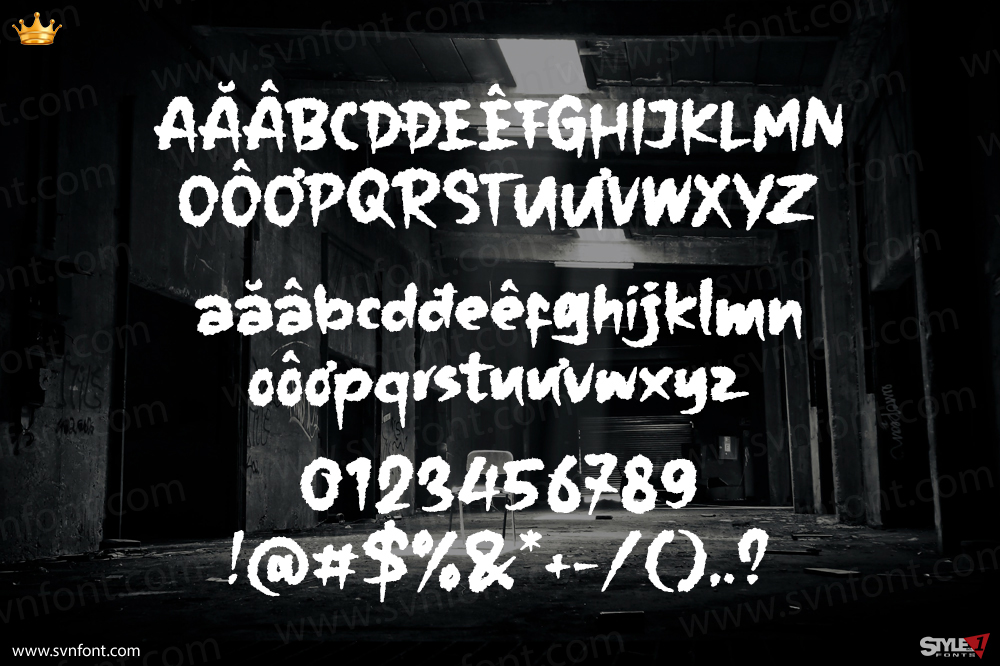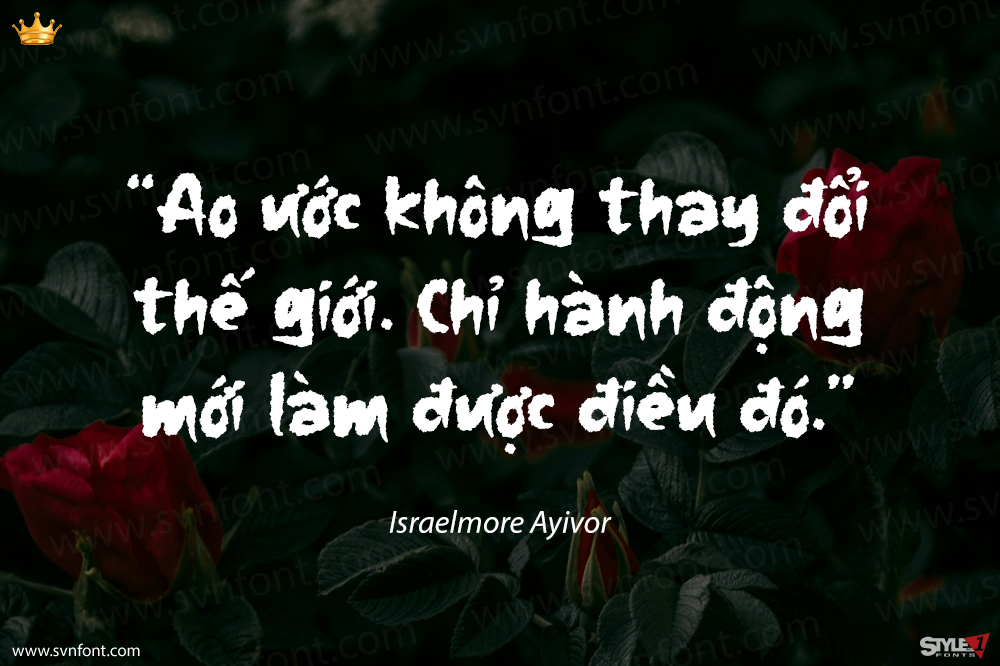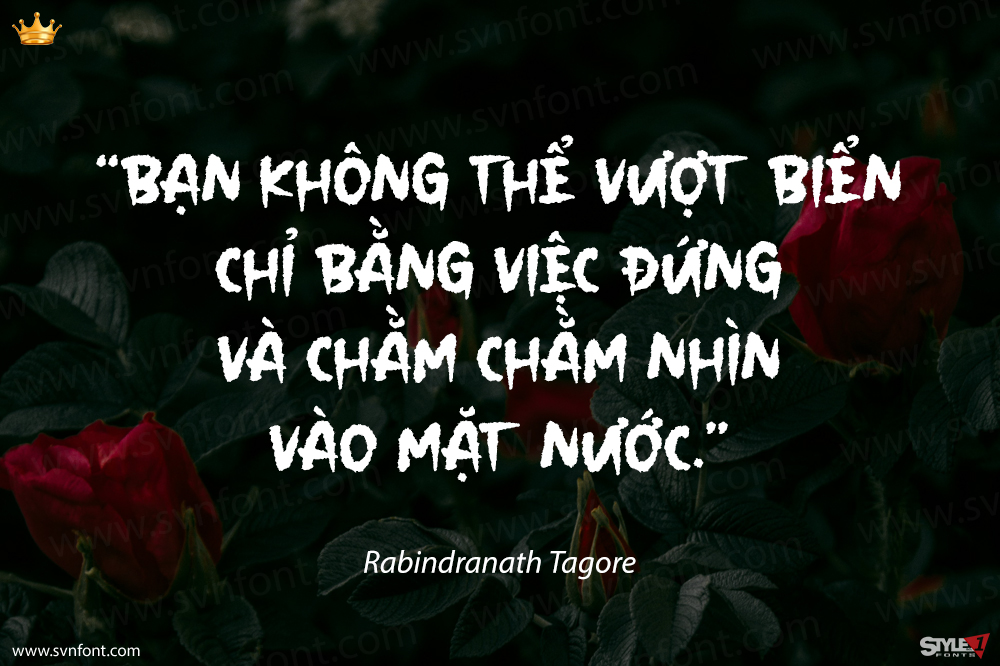
The Folacie | Phông Chữ Vẽ Tay Thô, từ Denustudios, phù hợp với mọi dự án như: logo, dự án xây dựng thương hiệu, thiết kế đồ gia dụng, bao bì sản phẩm, cốc, trích dẫn, áp phích, túi mua sắm, áo phông, bìa sách, danh thiếp, thiệp mời, thiệp chúc mừng, nhãn mác, nhiếp ảnh, hình mờ, sự kiện đặc biệt và tất cả các dự án đáng yêu khác của bạn cần một chút hương vị của Phông Chữ Vẽ Tay Thô.
Nhà thiết kế: Dede Nugraha
Nhà phát hành: Denustudio